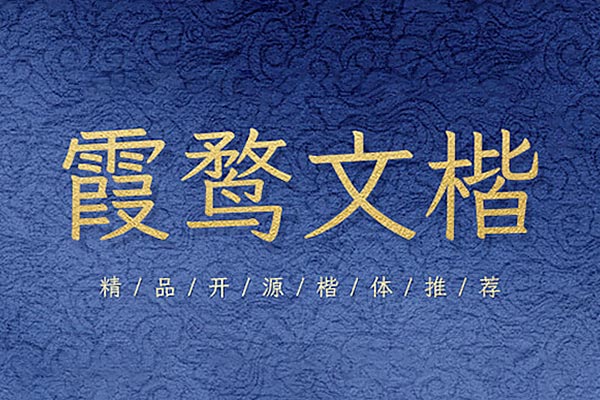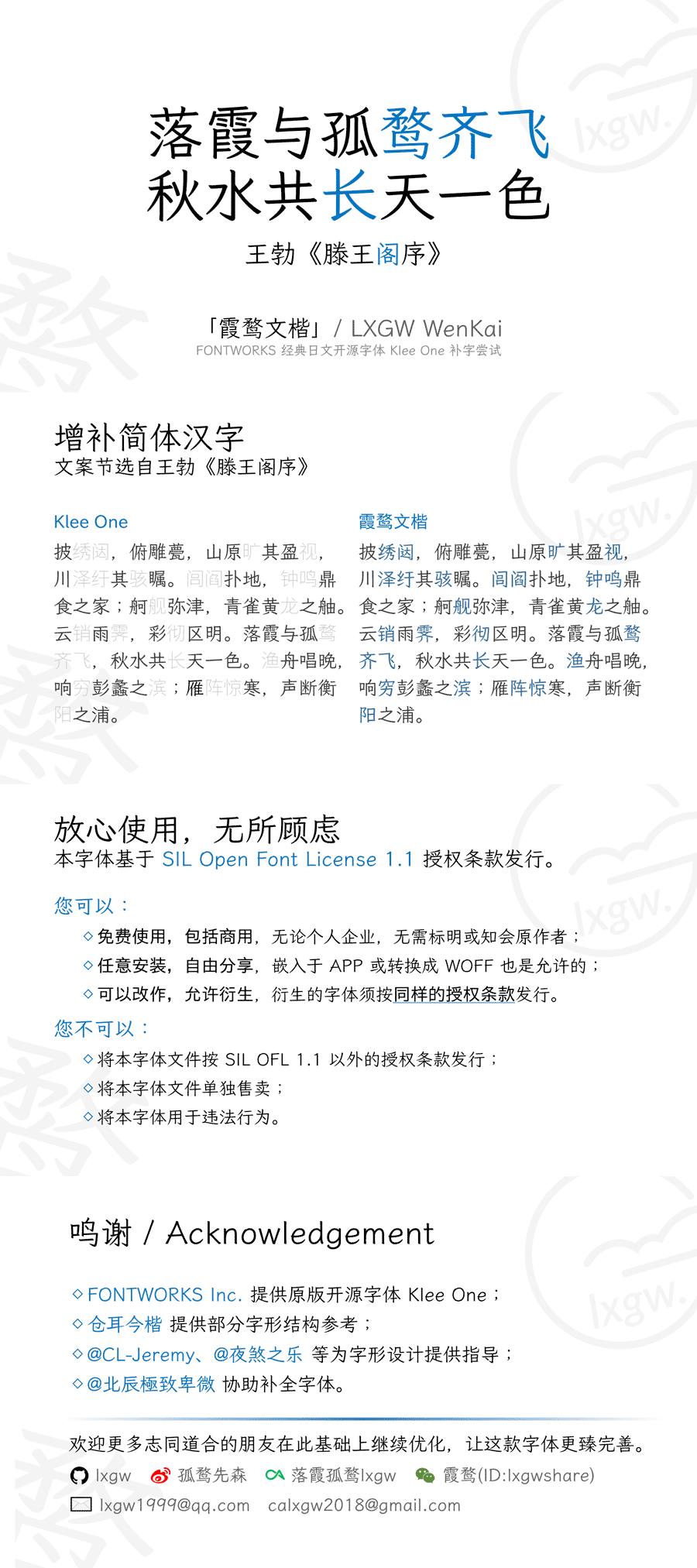
霞鹜文楷
霞鹜文楷是落霞孤鹜基于Klee One增补的开源中文字体,具有高可读性。日本Fontworks发布了7款开源日文字体,其中Klee具有教科书体和仿宋、楷体特点。一些爱好者用仿宋、刻本仿宋、仓耳今楷补全了这款字体,用于手机系统美化。但存在混排违和感和商业侵权风险。落霞孤鹜补全了GB2312的简体字和常用繁体字,满足了基本需求。该字体依据SIL Open Font License 1.1授权协议免费公开,可免费用于个人及商业用途。更新记录:2021-07-19至2022-04-20期间,霞鹜文楷进行了多次更新,扩展了字重,增加了等宽字体Mono版本,调整了80个字的字形。
霞鹜文楷效果预览
霞鹜文楷字体效果预览